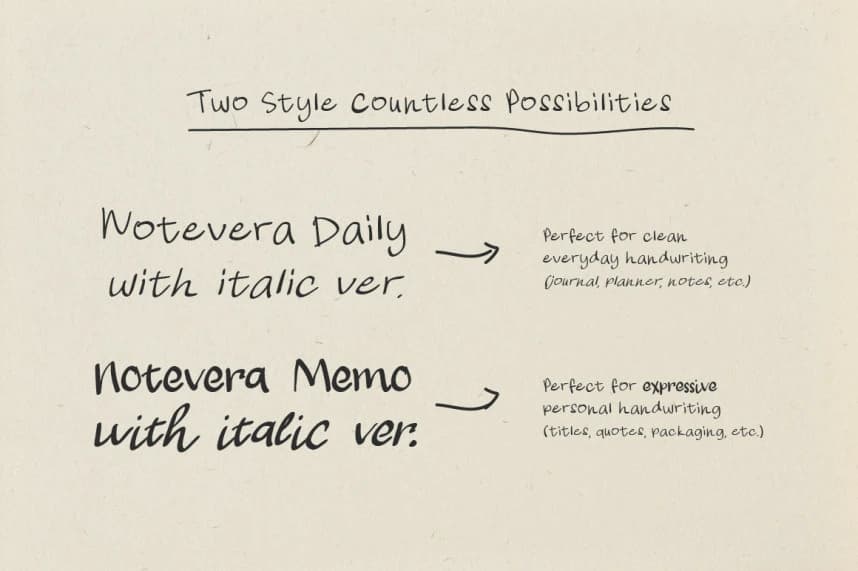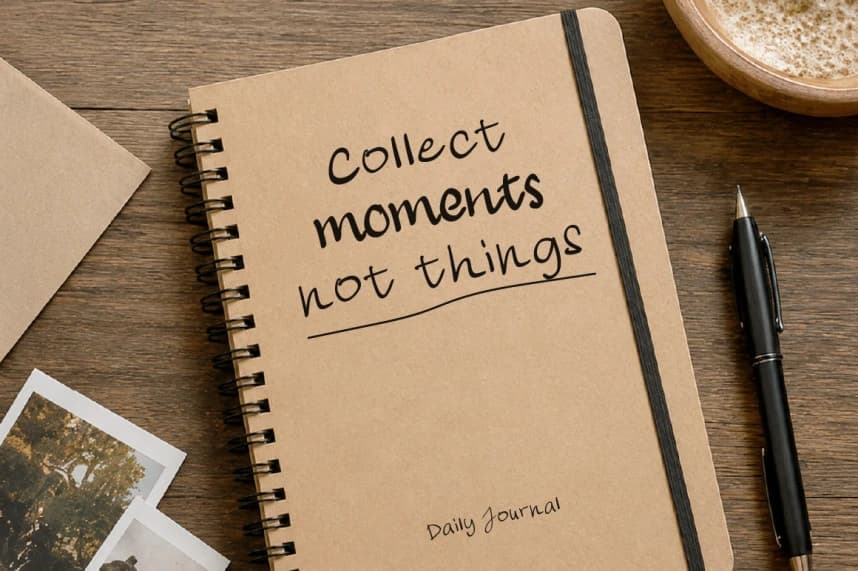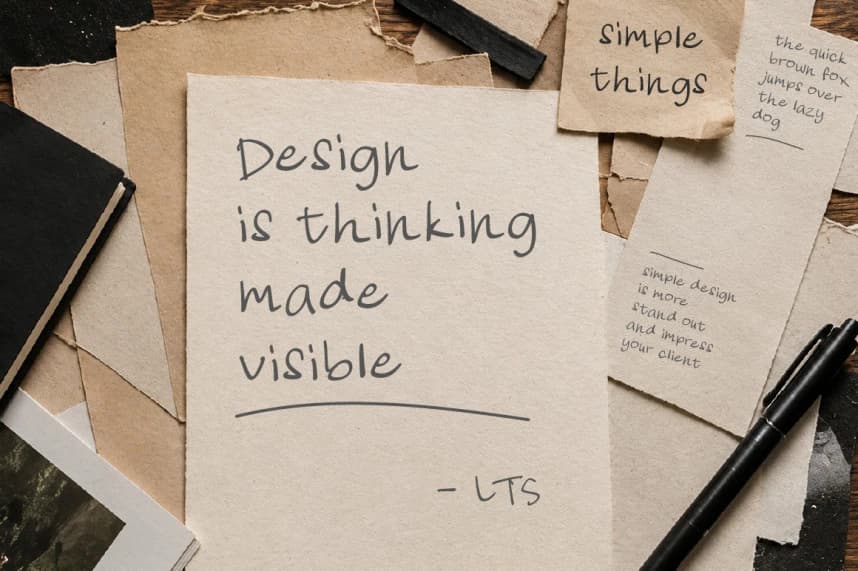
Notevera Duo Yazı Tipi
Notevera Duo Font, doğal yazının sıcaklığını temiz bir editoryal dokunuşla yakalamak için tasarlanmış modern bir el yazısı font ikilisidir. İki birbirini tamamlayan el yazısı stiline sahip olacak şekilde tasarlanmıştır — Notevera Daily ve Notevera Memo.
Notevera Duo Font, doğal yazının sıcaklığını temiz bir editöryal dokunuşla yakalamak için tasarlanmış modern bir el yazısı fontu ikilisidir. İki tamamlayıcı el yazısı stil ile tasarlandı — Notevera Daily ve Notevera Memo